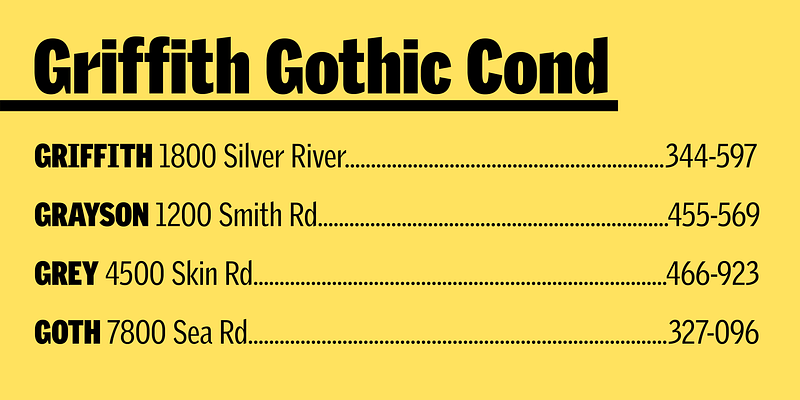
Diseñado por Chauncey Griffith en 1937 para su uso en guías telefónicas, Bell Gothic fue una bestia de carga probada para tamaños de texto. Griffith Gothic revive y expande el diseño para usarlo en titulares y texto, agregando varios grosores, además de cursiva y un rango condensado. Su drástico adelgazamiento de las juntas, originalmente pretendía prever la propagación de la tinta, continúa como una característica expresiva.